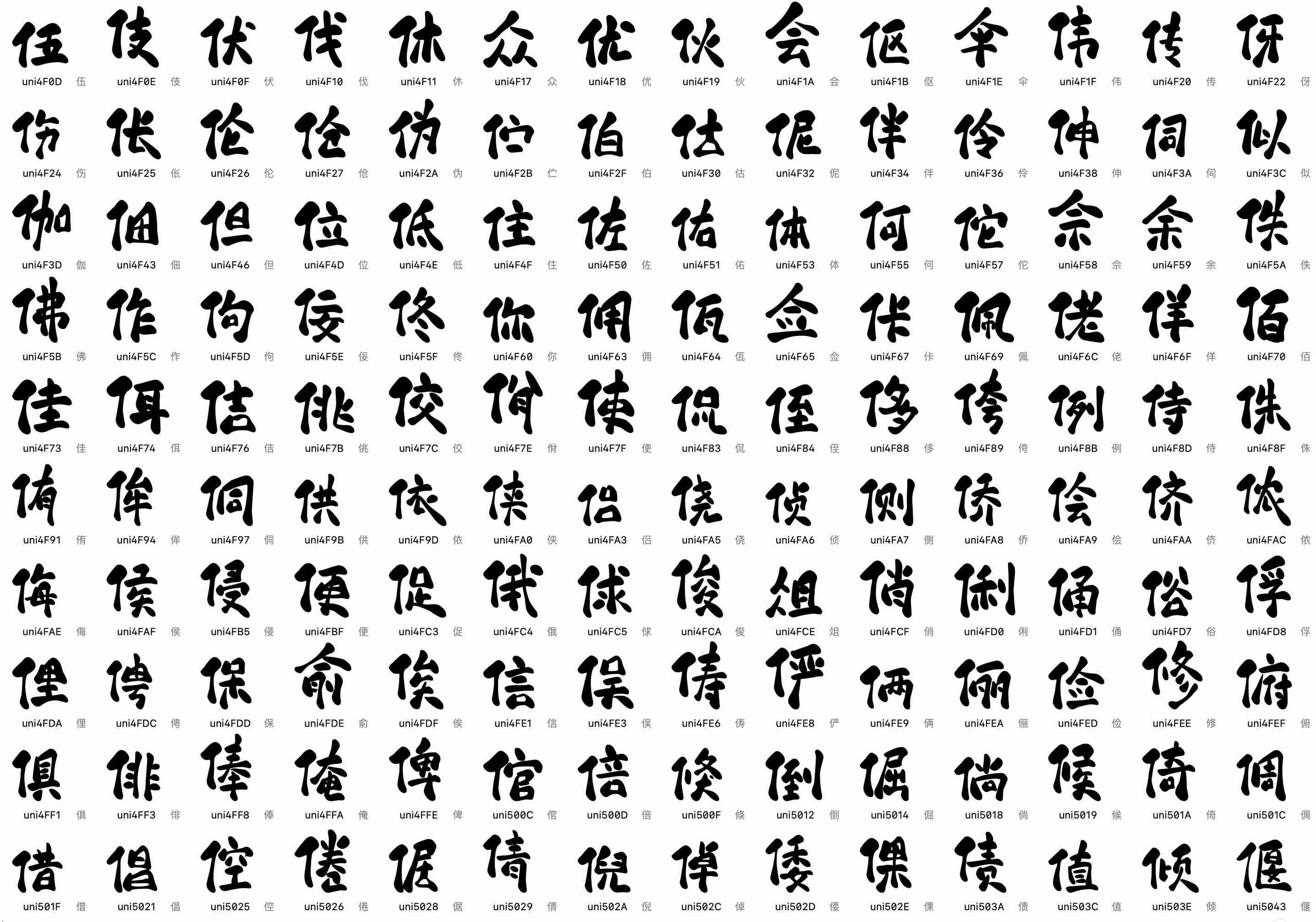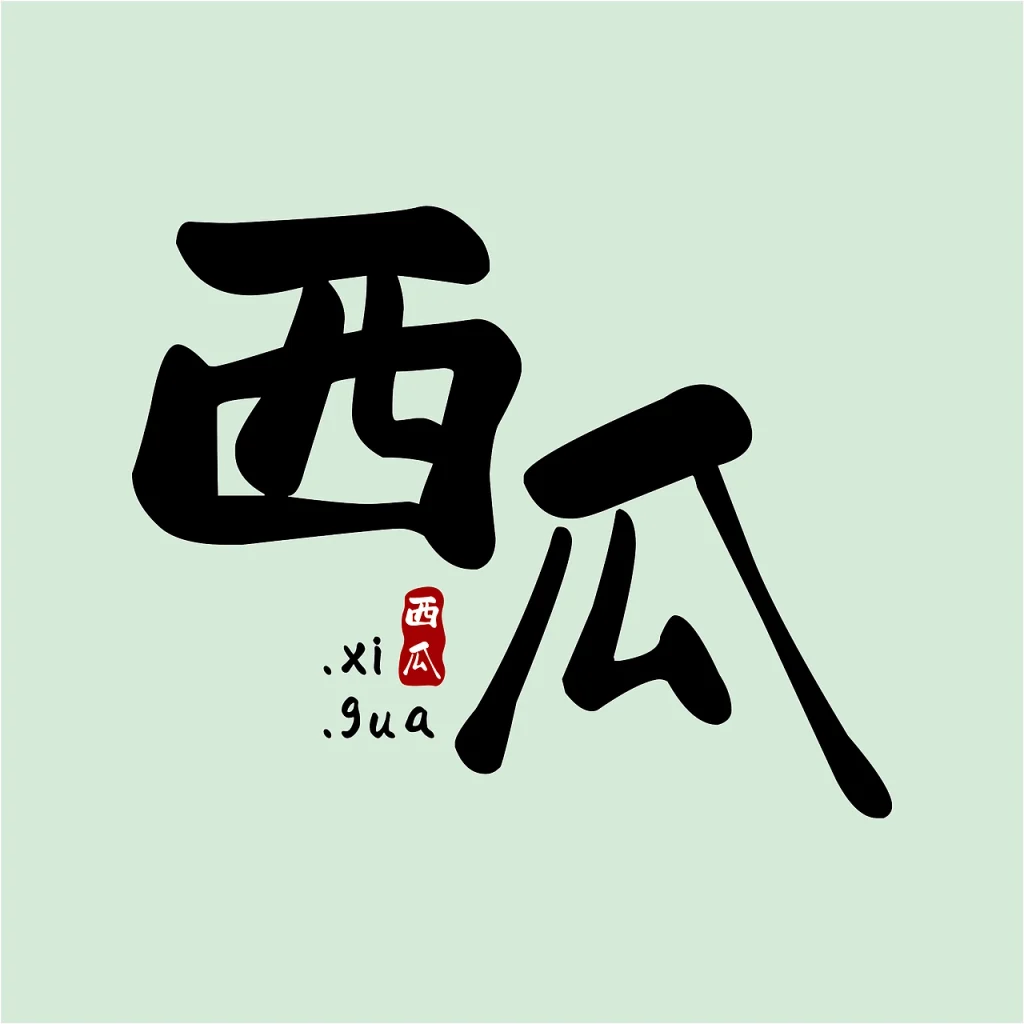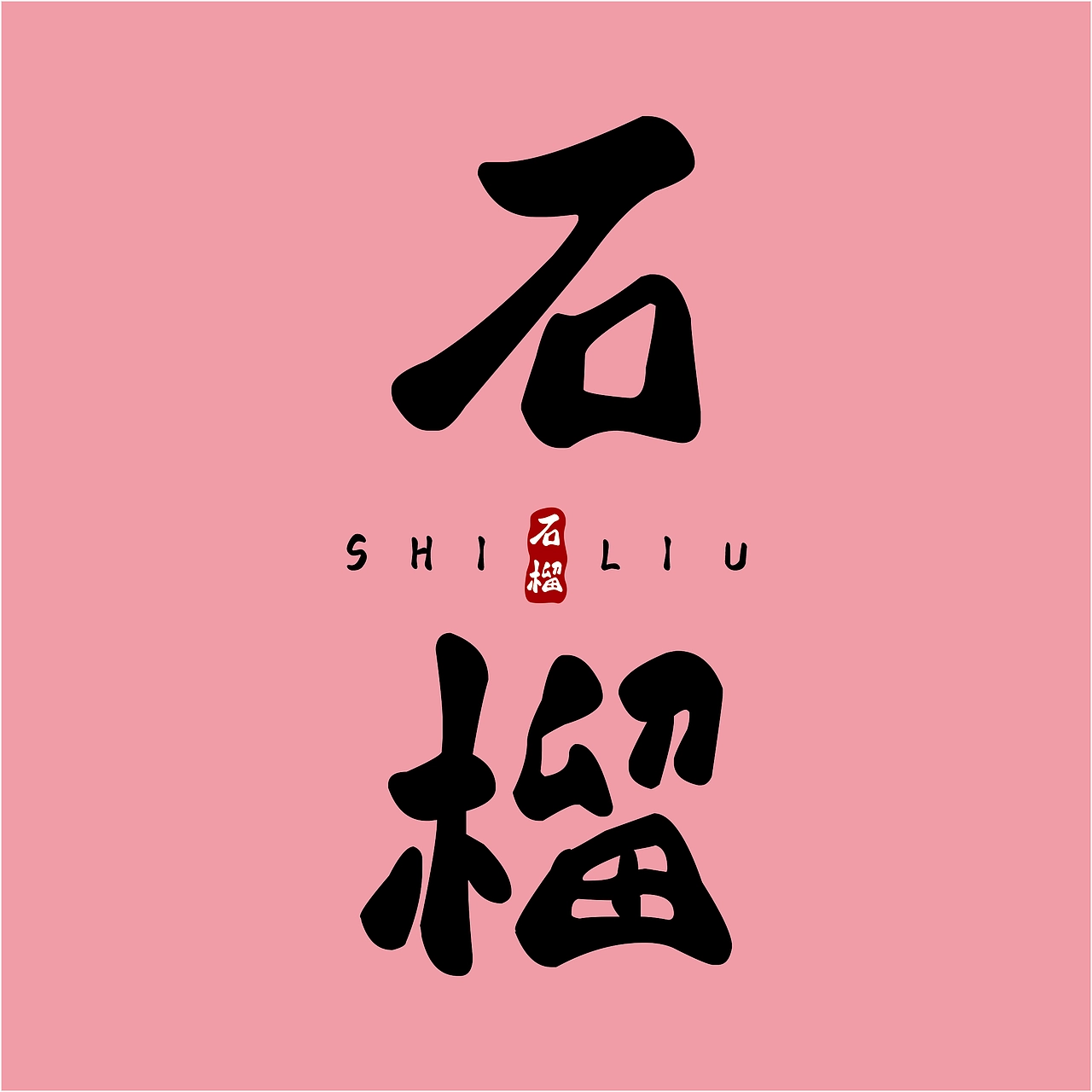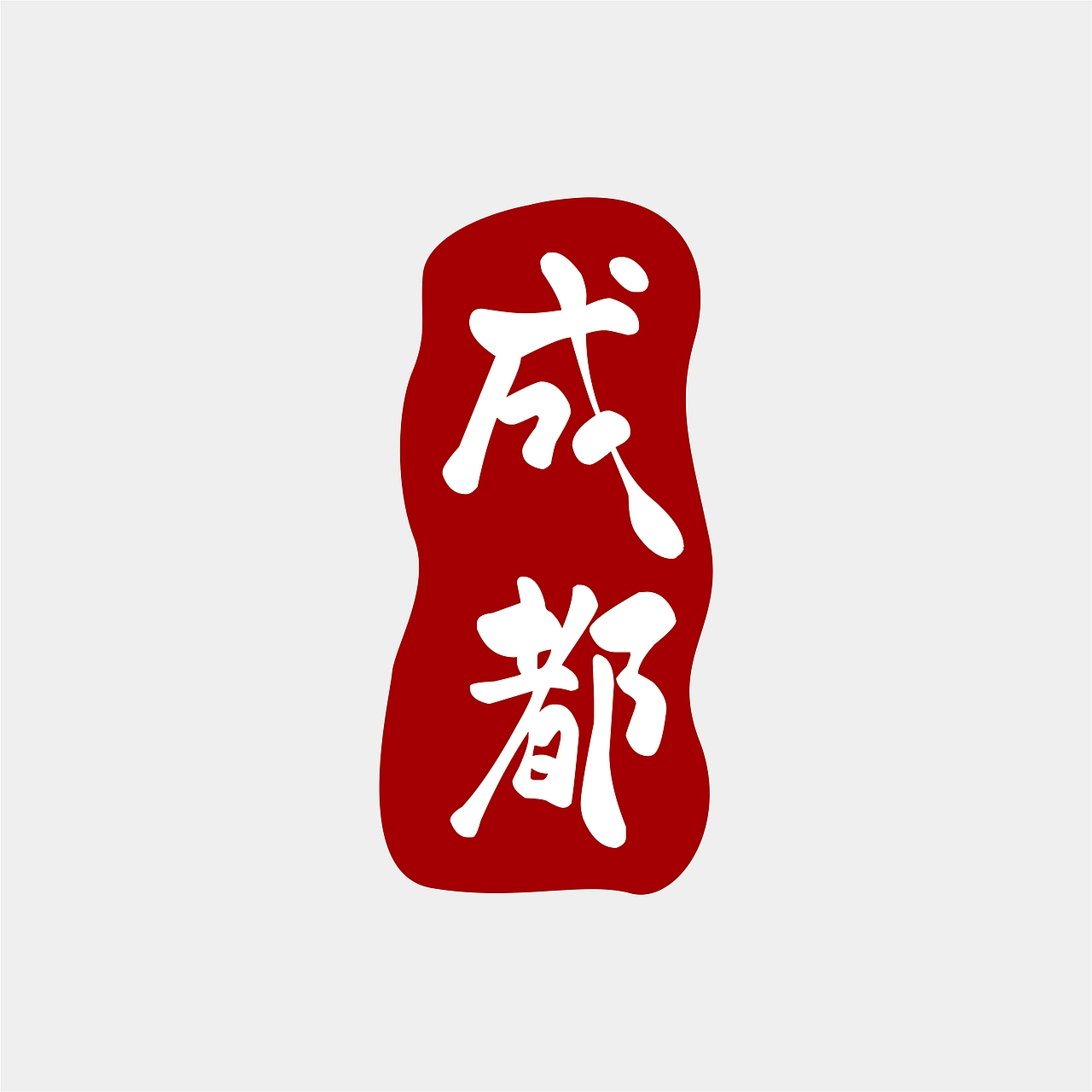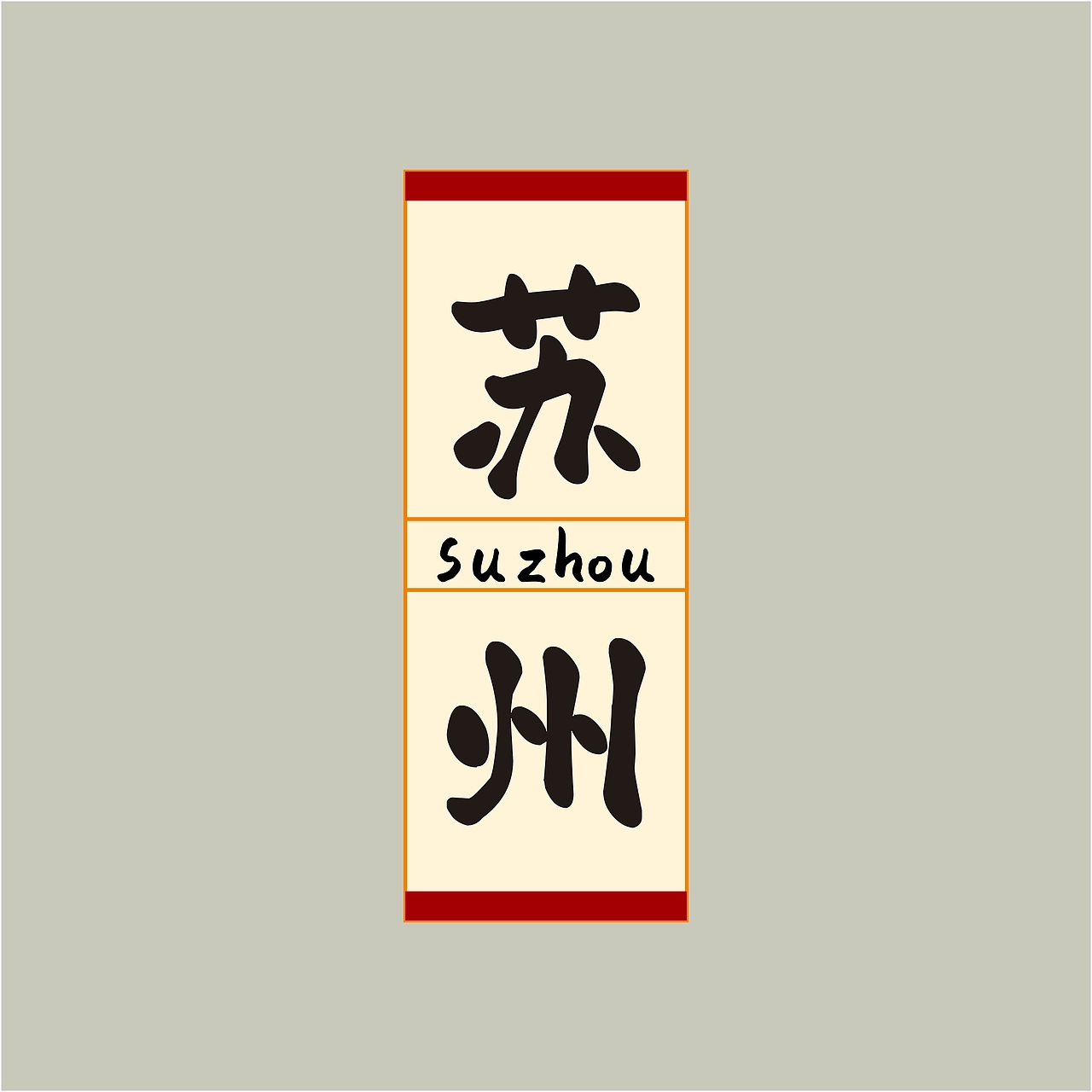
赖江湖墨暖圆书
赖江湖墨暖圆书是一款由赖江湖独立创作完成的中文手写字体,整体采用平板手绘方式设计,将日常书写中的自然笔触与轻松情绪融入数字字体之中。字体以柔和圆润的线条为主要特点,通过弱化尖锐转折、增加笔画圆角感,让文字呈现出更加温暖、亲切且富有生活气息的视觉效果。
在字体设计上,赖江湖墨暖圆书没有刻意追求传统书法字体的强烈力量感,而是更加注重手写过程中的随性感与松弛感。字体笔画饱满流畅,边角经过圆润处理,整体造型带有轻松自然的卡通氛围。相比规整的印刷字体,这款字体保留了手写文字独有的不规则变化,让每一个字都拥有更加鲜活的个性与温度。
赖江湖墨暖圆书在保持手写风格的同时,也兼顾了文字的识别性与实用性。字体结构自然舒展,大小字号均具备较好的阅读表现,无论用于标题展示、短句排版还是视觉设计中的文字点缀,都能够呈现出轻松活泼的效果,为作品增添更加亲和的视觉气质。
凭借柔和、可爱的字体风格,赖江湖墨暖圆书适用于多种设计场景,包括短视频字幕、海报标题、儿童文创、包装设计、手账排版、电商视觉、PPT设计以及门店宣传等。无论是打造年轻化品牌形象,还是营造温暖、有趣的内容氛围,这款字体都能够带来更加自然的表达效果。
总的来说,赖江湖墨暖圆书不仅是一款数字字体,更是作者对于日常书写情绪的一次记录与转化。它将平板创作中的自由笔触转变为具有设计价值的字体语言,让文字在保持实用性的同时,也拥有更加柔软、生动的视觉魅力。